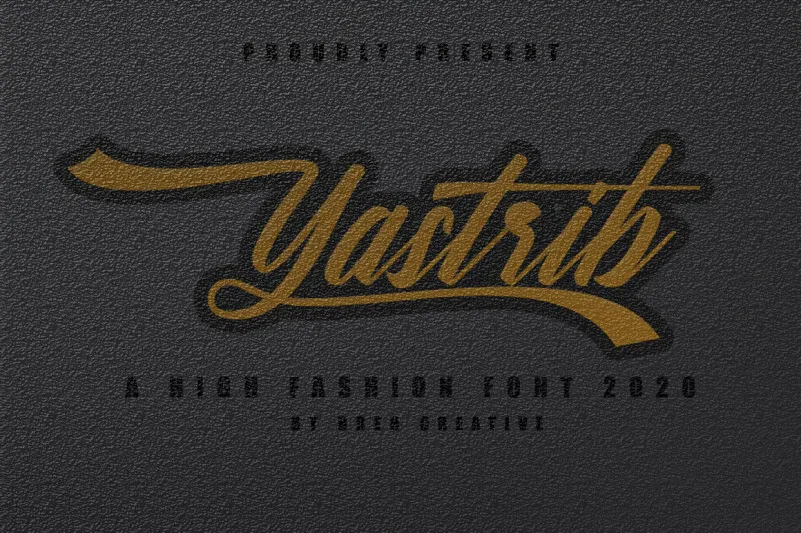
Yastrib Script Font – Download Grátis
A Yastrib Script Font é uma preciosidade para designers e criativos do Brasil. Com seu estilo vintage encantador, esta fonte pode transformar qualquer design de produto, etiqueta de casamento ou marca de roupas em algo único e elegante. Além disso, é perfeita para as criações vintage que você já está planejando. Foi criada pela BrehCreative e traz uma mistura única de elegância e nostalgia, tornando-a uma escolha ótima não apenas para os usuários brasileiros, mas também para aqueles que valorizam o design local. Seja para criar um design simples ou um conceito complexo, esta fonte é versátil e será um excelente adição a seu arsenal de ferramentas digitais.